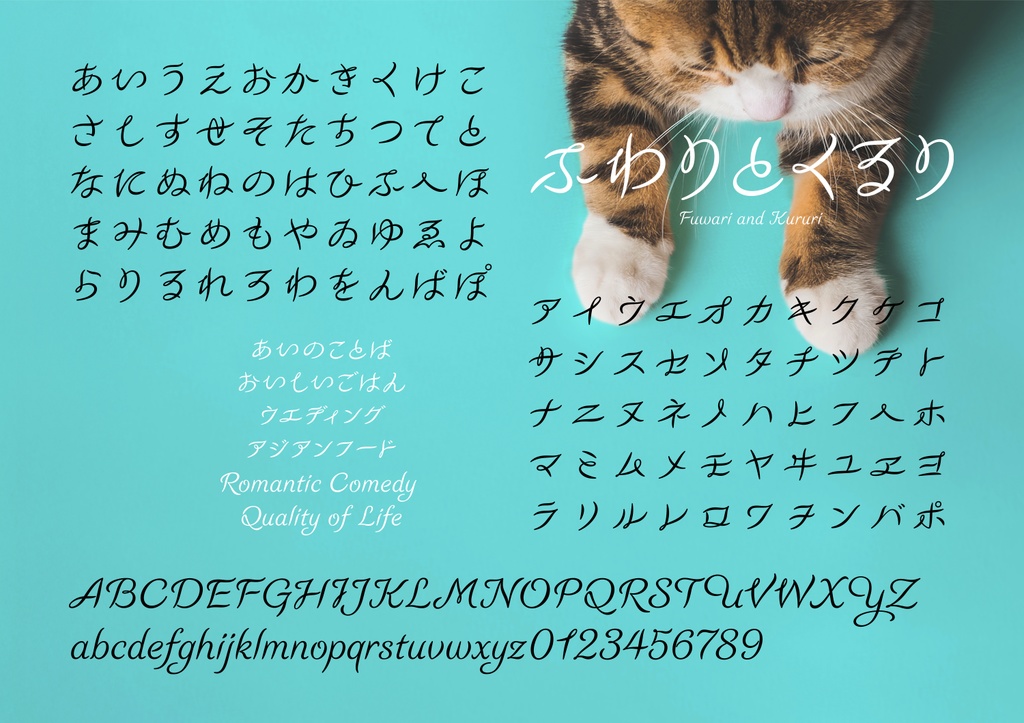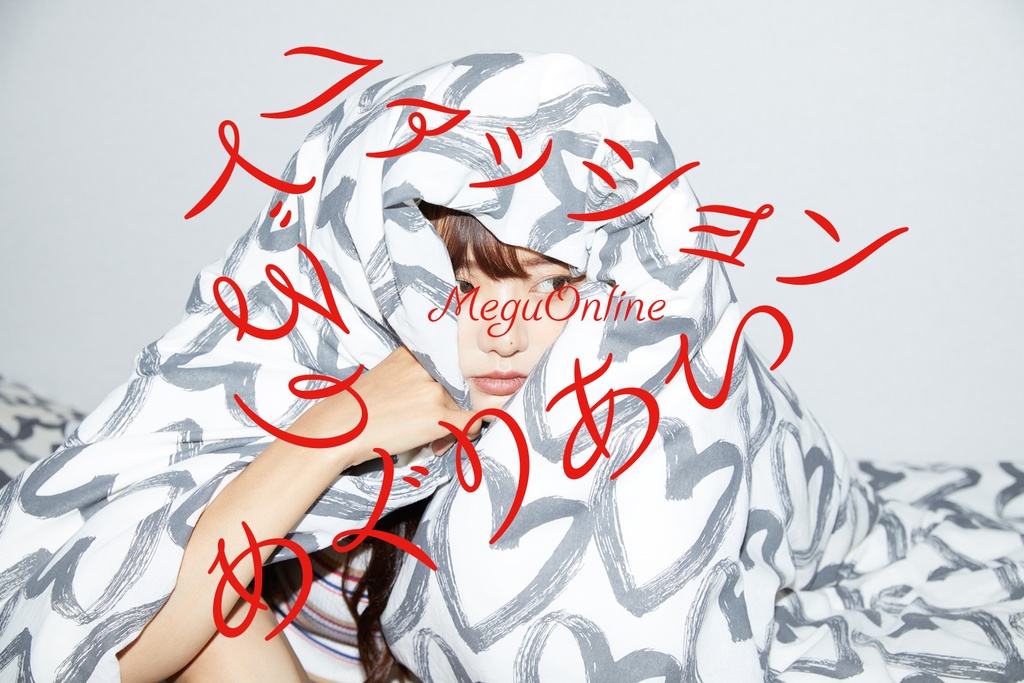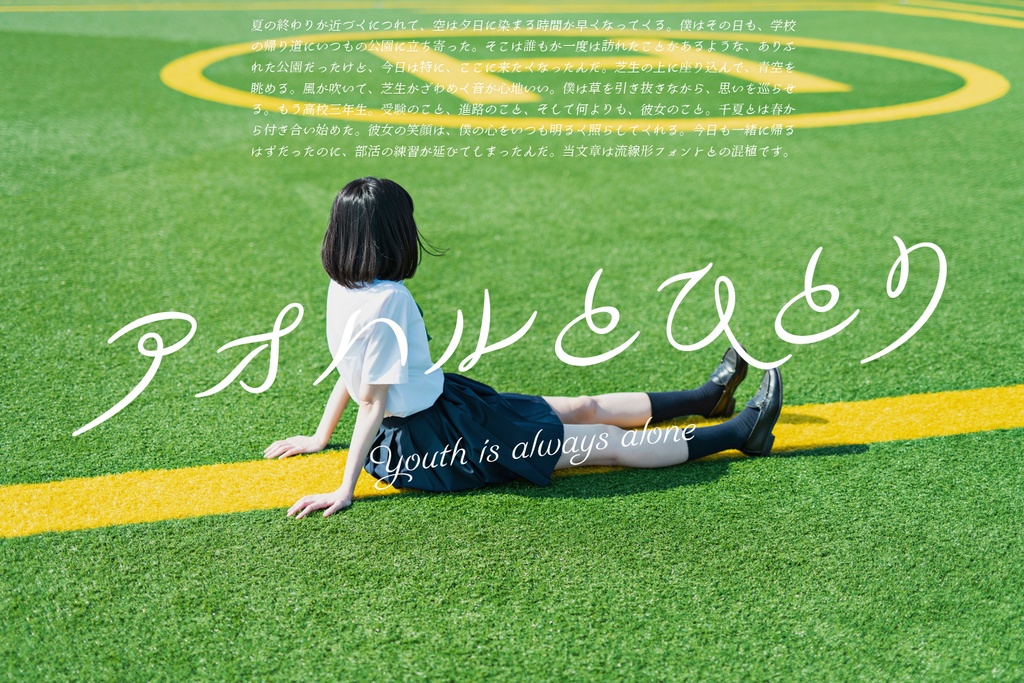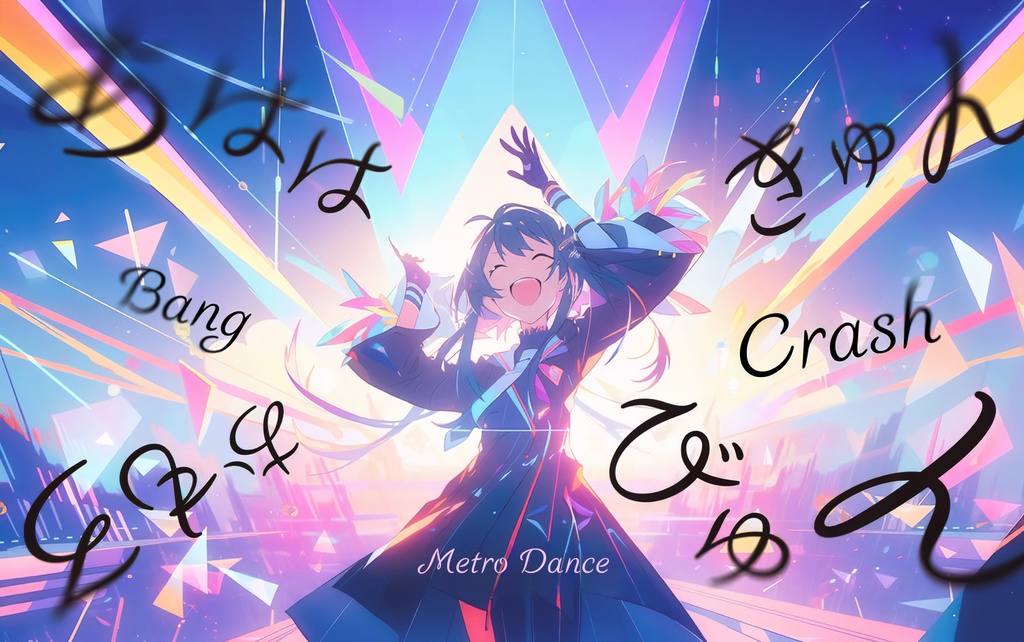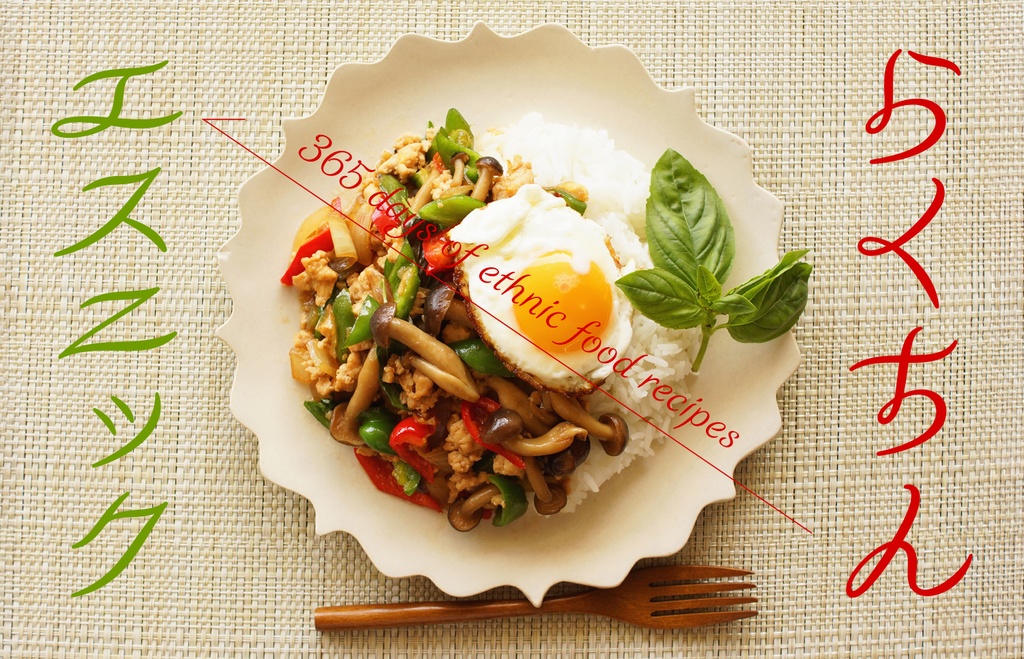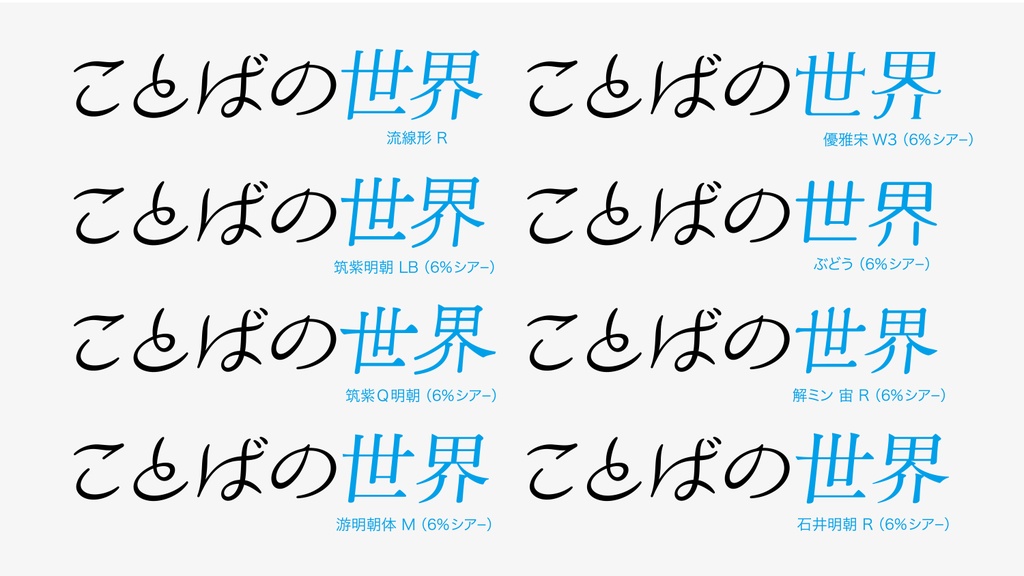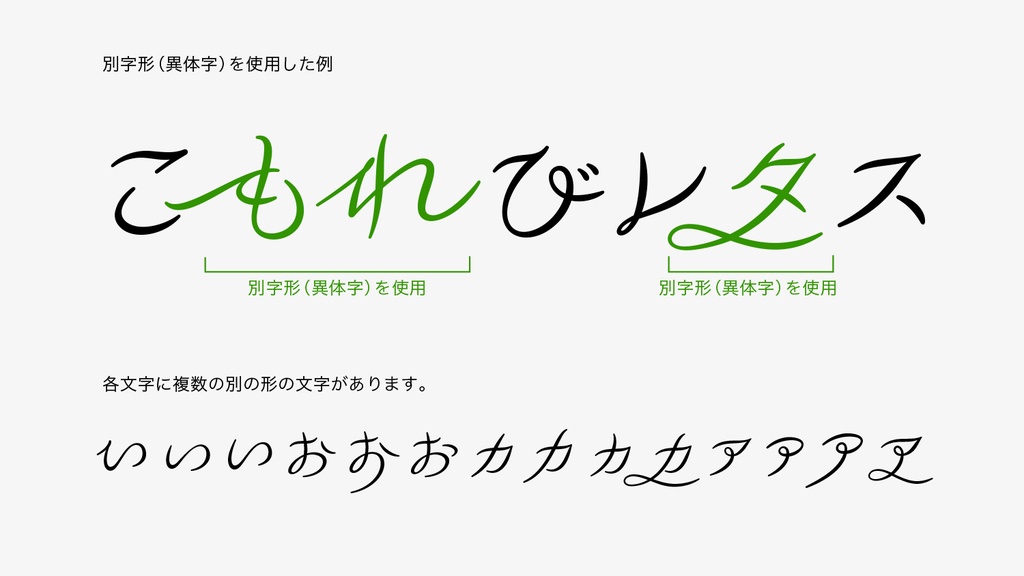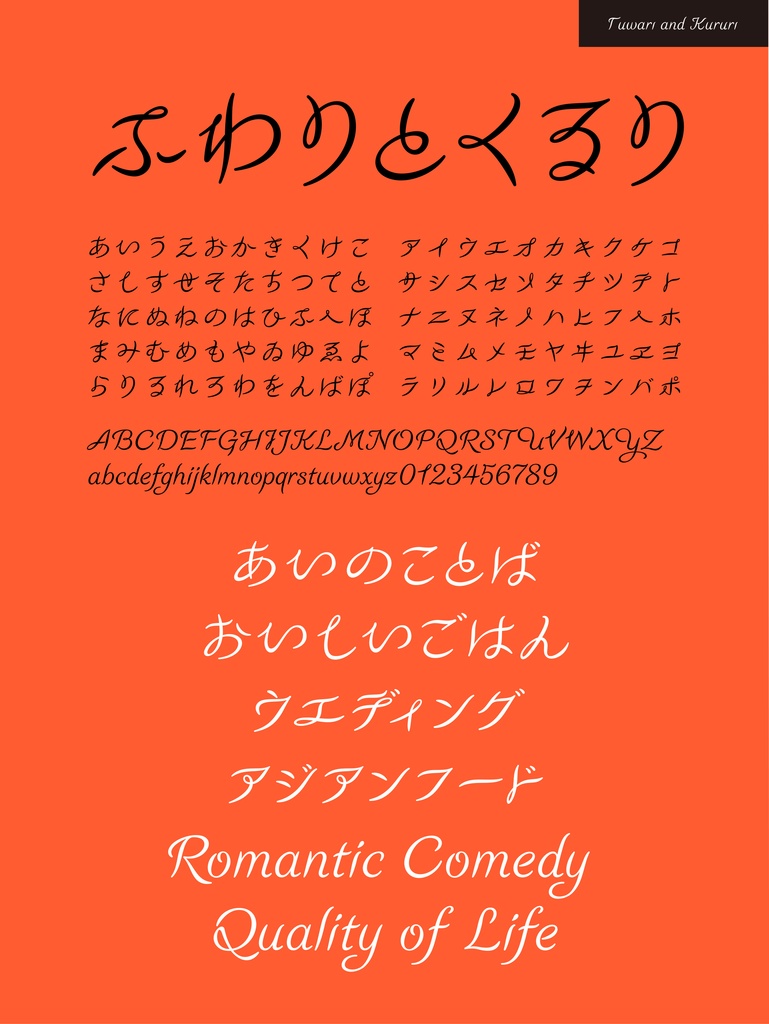
ふわりとくるり フォント
ふんわりとした優雅なカーブとくるりと回転する動きが特徴的なデザイン書体。全ての文字が欧文に合わせて斜体になっています。なめらかな曲線を活かしたエレガントなデザインやエスニックなロゴタイプなど、幅広い用途で活躍。遊び心のあるデザインは使うだけで楽しい世界観を生み出します。
■収録文字について
収録文字数700字。※収録文字はアルファベット、ひらがな、カタカナ、約物の一部。
■OpenType機能
詰め組み機能
ペアカーニング(仮名・プロポーショナル欧文)
字形切り替え機能(異なる字形を326種用意しています)※字形切り替えが使えないソフトウェア用に追加のPDFデータを用意しています。